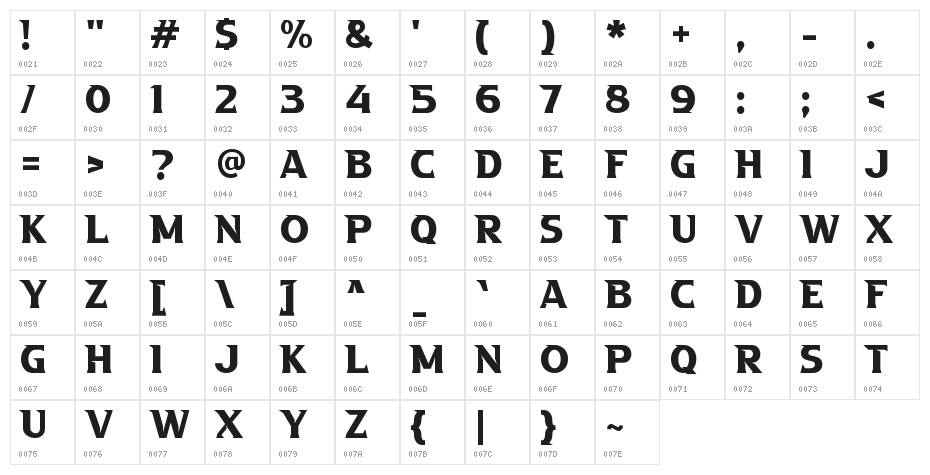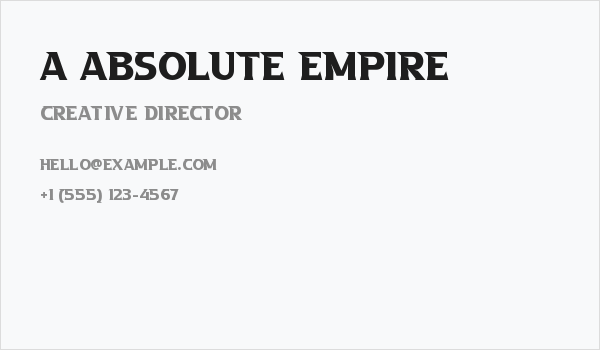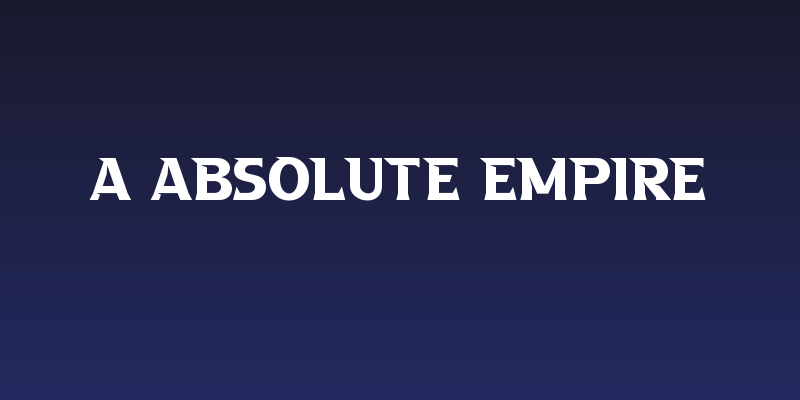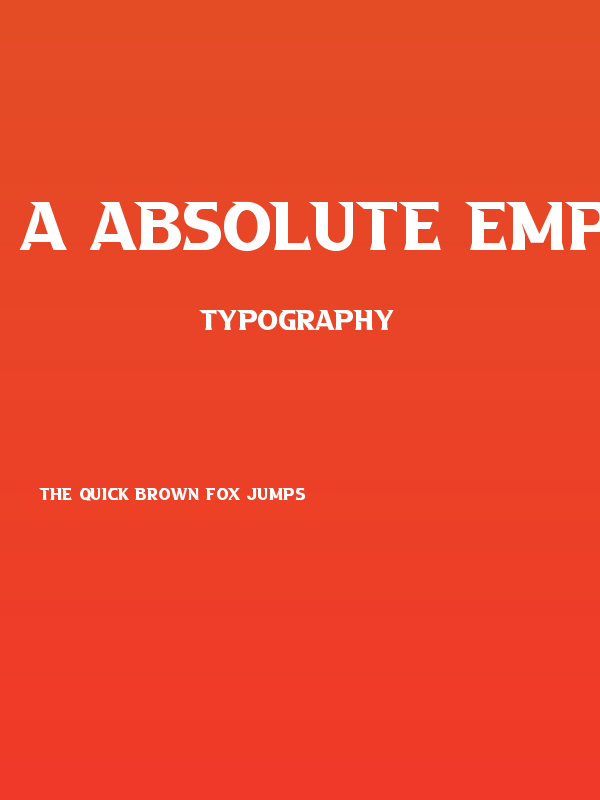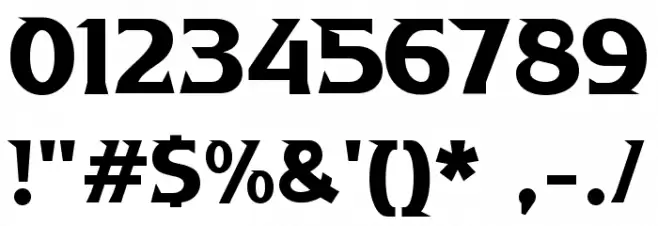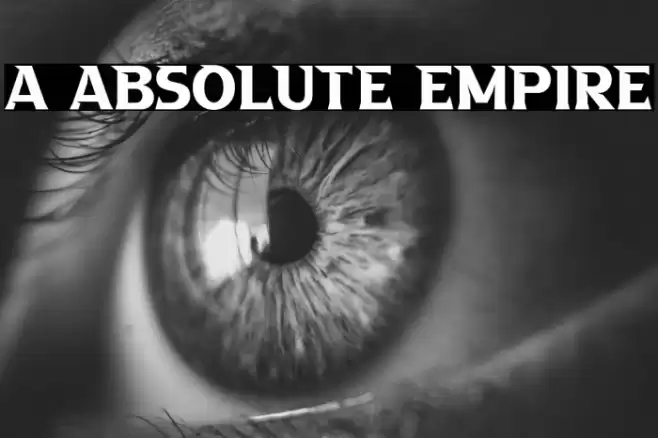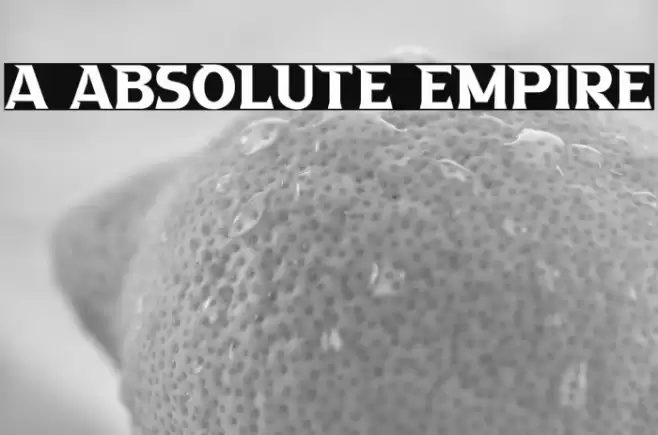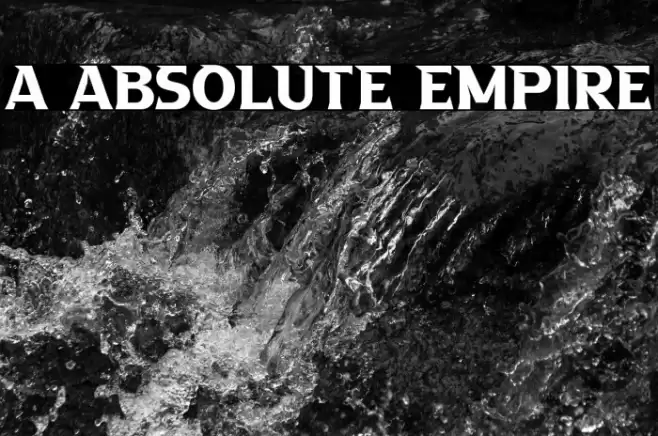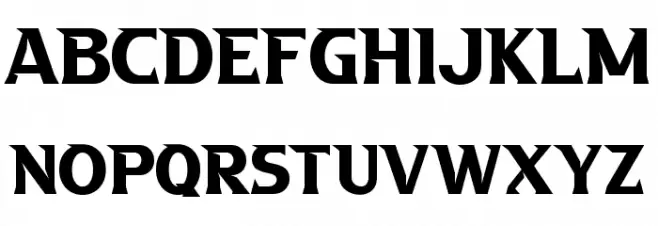
a Absolute Empire Font
✎ Serif
| Projets proposés | This font is perfect for projects that require a strong visual impact, such as branding, advertising, and editorial headlines. It can also be used effectively in logo design and promotional materials. |